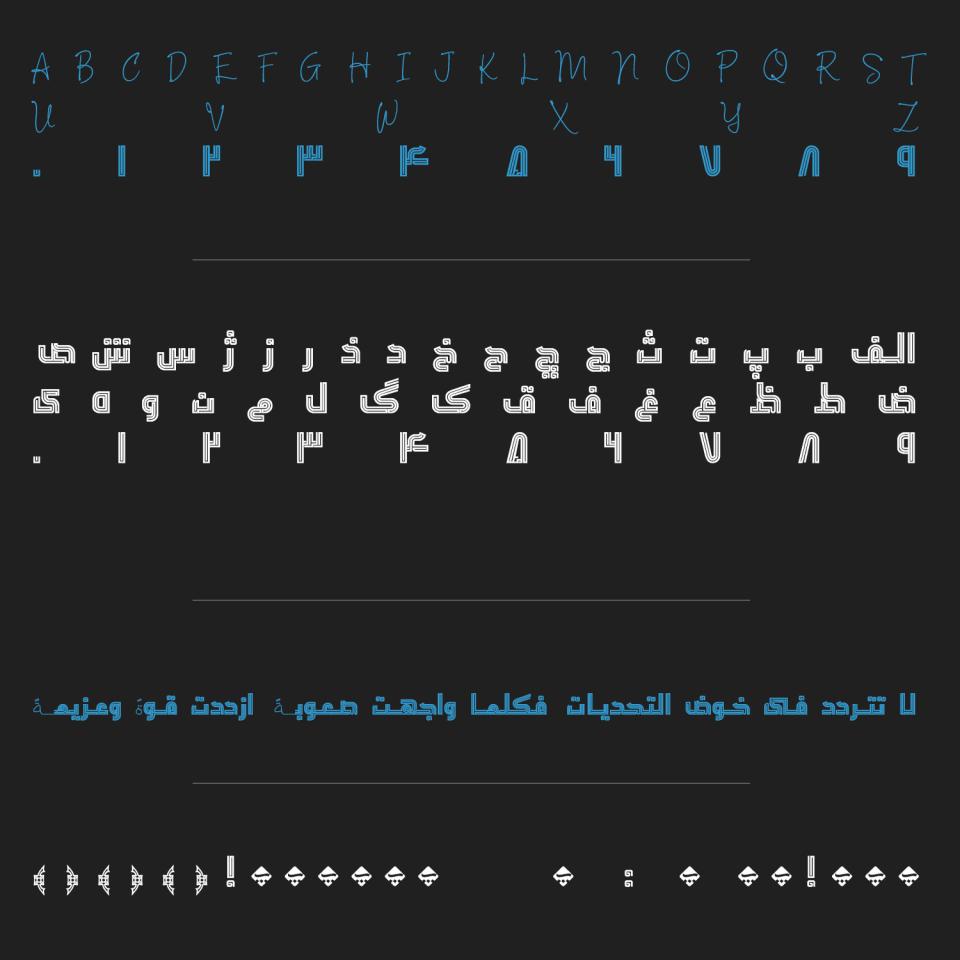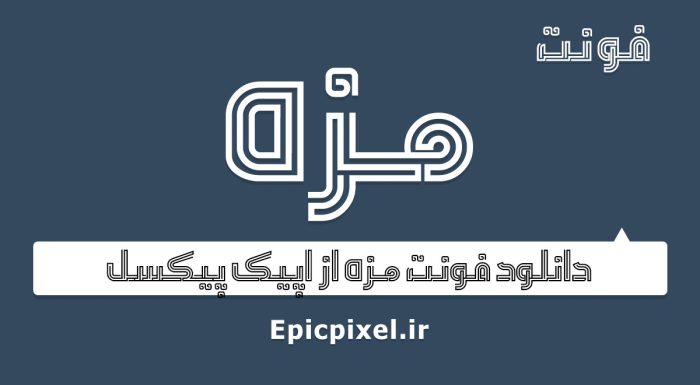
فونت مزه فارسی Maze
فونت مزه، با ظاهری فانتزی و ساختاری هندسی، تجربه ای متفاوت از تایپ فارسی را ارائه می دهد. این فونت با خطوط صاف و کشیده و در عین حال منحنی های نرم و صیقل خورده طراحی شده که خوانایی بالایی را به ارمغان می آورد. طراحی چند خطی داخل حروف، ویژگی منحصربه فرد این فونت است که به آن جلوه ای خاص و چشم نواز می بخشد و آن را از سایر فونت ها متمایز می کند. این ویژگی در عین زیبایی، ممکن است در اندازه های بسیار کوچک، کمی از خوانایی آن بکاهد، اما در مجموع، فونت مزه برای طراحی های گرافیکی، عناوین جذاب و استفاده در فضاهای مجازی، گزینه ای ایده آل است.
این فونت به دلیل ساختار هندسی خود، حس مدرن و امروزی را القا می کند و در عین حال، با داشتن خطوط منحنی، از خشکی فونت های کاملاً هندسی فاصله گرفته و حس صمیمیت و دوستانه تری را منتقل می کند. اگر به دنبال فونتی هستید که هم جذابیت بصری داشته باشد و هم خوانایی مناسبی ارائه دهد، فونت مزه انتخاب خوبی خواهد بود. به راحتی می توانید این فونت را دانلود و در پروژه های خود استفاده کنید.